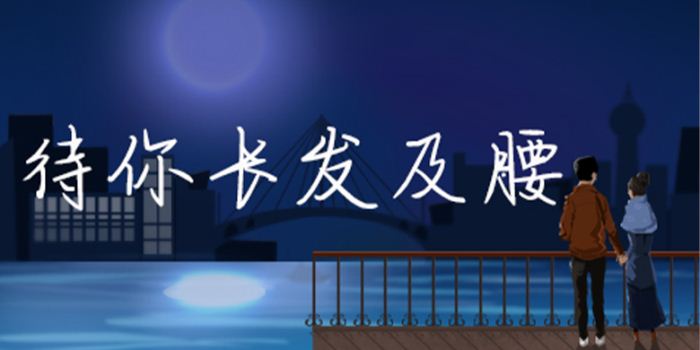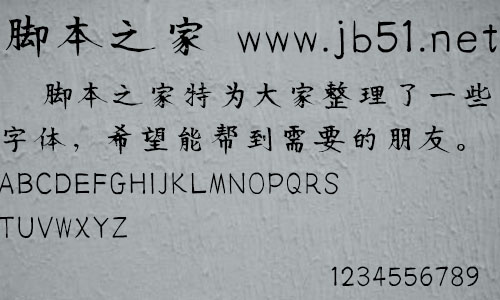
方正手跡-待你長發(fā)及腰由方正字庫劉殿儒設(shè)計師出品的藝術(shù)字體,字體整體偏瘦,清新時尚,筆畫走勢自然舒展,充滿青春文藝的感覺,適合應(yīng)用于藝術(shù)設(shè)計、平面宣傳設(shè)計、網(wǎng)頁設(shè)計,書法等領(lǐng)域。
方正手跡-待你長發(fā)及腰是一款富有青春氣息的手寫體。該字體整體偏瘦,清新時尚,筆畫走勢自然舒展,充滿青春文藝的感覺。該字體適用于文藝類的書刊、品牌廣告和產(chǎn)品包裝設(shè)計,以及社交網(wǎng)絡(luò)的個性化用字。。